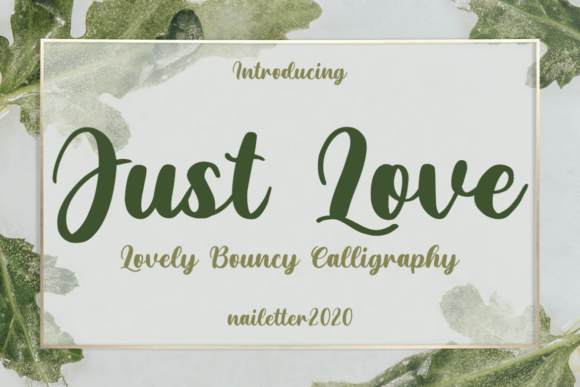
Just Love
Việc tìm kiếm các thành phần thiết kế phù hợp có thể là một thách thức, nhưng Just Love cung cấp một bộ sưu tập đặc biệt giúp nâng tầm công việc của bạn ngay lập tức.
Được chế tác với độ chính xác cao, Just Love cung cấp các vector sạch, kiểu chữ mượt mà và giấy phép thương mại để bạn yên tâm.
Cho dù bạn đang tạo sản phẩm POD (In theo yêu cầu), thiệp mời đám cưới hay đồ họa mạng xã hội, Just Love đều là một sự lựa chọn lý tưởng.